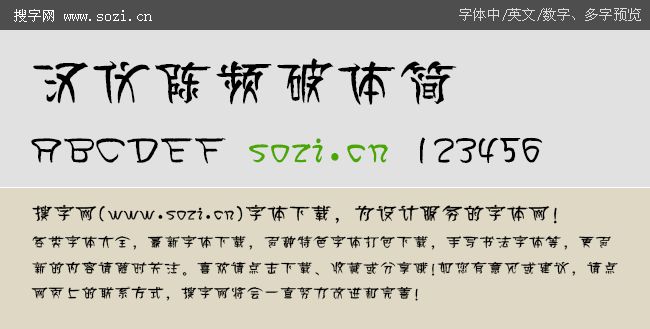
漢儀陳頻破體簡
搜字網(wǎng)給大家提供一款漢儀陳頻破體簡體藝術(shù)字體下載。漢儀陳頻破體簡是陳頻先生專創(chuàng)的字體,結(jié)構(gòu)新穎、風(fēng)格獨特;在固定的格柵中,呈倒梯形,布局合理、空白均勻;在注意結(jié)構(gòu)變化的同時強調(diào)協(xié)調(diào)一致性;筆畫的粗細(xì)富于變化,豎呈弧形,與字搭配協(xié)調(diào),在不影響易讀性的情況下,參入篆書的寫法;通篇看來規(guī)整劃一、韻味十足?蓱(yīng)用于平面廣告、印刷包裝、廣告創(chuàng)意、網(wǎng)頁設(shè)計等領(lǐng)域。